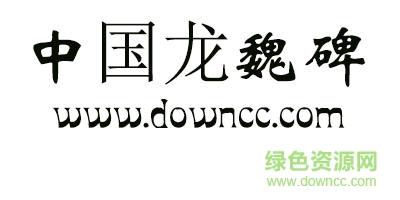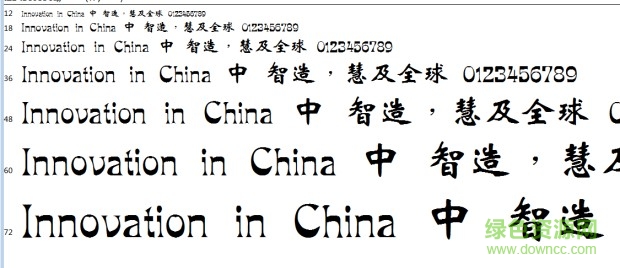
中國龍魏碑體是一款非常多人使用的中國龍字體之一,這款字體擁有別樣的字形風(fēng)味。歡迎來來綠色資源網(wǎng)下載體驗(yàn)。
1、橫畫和捺畫保持隸書的特點(diǎn),常伸展到字形邊界甚至超出邊界;字形與隸書相比呈扁方形;
2、橫畫和捺畫保持隸書的特點(diǎn),常伸展到字形邊界甚至超出邊界;
3、突出的特點(diǎn)是撇捺向兩側(cè)伸展,收筆前的粗頓以及抬峰,使整個(gè)字形厚重穩(wěn)健略顯飛揚(yáng)、規(guī)則中正而有動(dòng)態(tài),頗具審美價(jià)值。